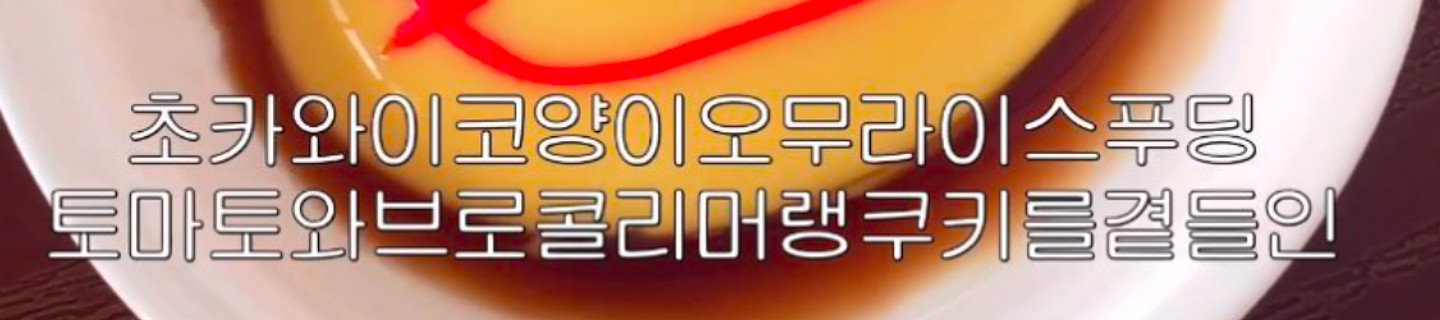
은 디나루
이전에 말씀드린 바와 같이 원래는 굵은 폰트이지만 외곽선 효과로 굵기가 얇아 보이게 될 수 있습니다. https://kldp.net/unfonts/release (2607-un-fonts-core-1.0.2-080708.tar.gz)
친근하고 귀여운 손글씨 스타일: 정돈된 디지털 폰트보다는 사람이 손으로 직접 쓴 듯한 자연스럽고 따뜻한 느낌을 주는 서체입니다. 둥근 모서리 처리: 거의 모든 획의 끝부분이 각지지 않고 부드럽게 둥글게 처리되어 있어 전체적으로 유하고 다정해 보입니다. 일정한 굵기: 각 글자를 구성하는 획의 굵기가 대부분 일정하며, 굵은 붓펜이나 두꺼운 사인펜으로 쓴 듯한 안정감을 줍니다. 높은 가독성: 손글씨 스타일임에도 불구하고 각 자음과 모음의 형태가 뚜렷하게 구분되어 있어 읽기가 매우 쉽습니다.